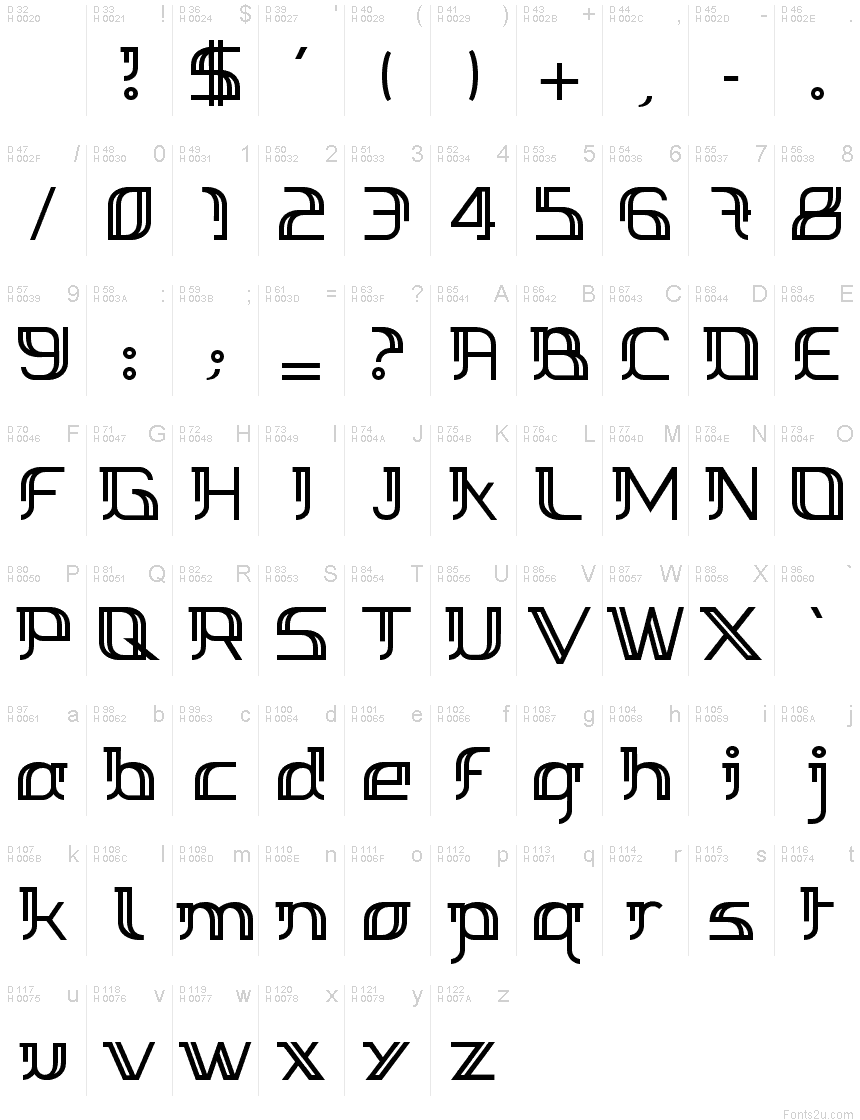
Margarette 01 è un carattere display futuristico gratuito, costruito su archi ampi e tratti verticali dal controllo rigoroso. La sua M geometrica sovradimensionata e le forme arrotondate ricorrenti evocano il lettering dell'era spaziale con un tocco raffinato e di tendenza, mentre le giunture strette mantengono un ritmo architettonico e teso.
Il contrasto tra le curve ampie e la finezza dei dettagli verticali crea una silhouette drammatica, ideale per sistemi di identità visiva ed editoriali di moda. Utilizza questo font gratuito per grafiche musicali, sequenze di titoli, poster di eventi o packaging elegante quando il progetto richiede un'eleganza retro-futurista piuttosto che un mood sci-fi meccanico.
Margarette 01